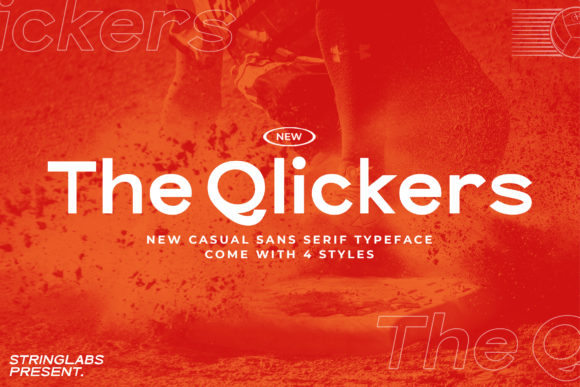
Creativefabrica The Qlickers Font
[Creativefabrica] The Qlickers Font
Qlickers - это крутой, уверенный и непринужденный шрифт без засечек.
Он будет выглядеть потрясающе на любой плакатной листовке или принтере.
Используйте этот шрифт для ваших дизайнов и изучите его бесконечные возможности.